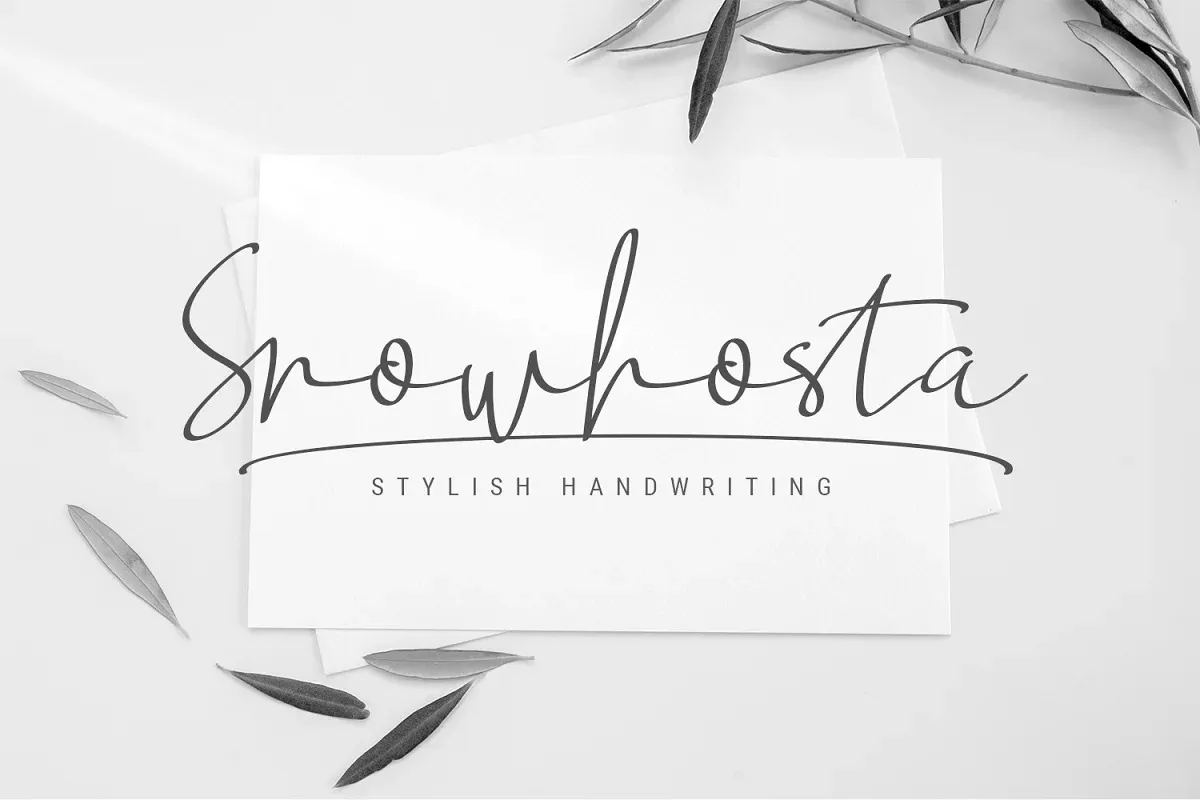
A fonte Snowhosta é uma elegante e bem equilibrada fonte de script, cuidadosamente criada pela Fontcastle para designers apaixonados por estilo moderno. Cada letra exibe um toque único e belo, garantindo que seu design brilhe com vida. Definida por curvas suaves e perfeitas para o branding fashion ou editoriais, Snowhosta encanta seus usuários com sua autenticidade. Este é um ótimo recurso para quem quer criar cartões de agradecimento adoráveis, artes de estação elegantes, postagens em redes sociais chamativas e convites de casamento incrivelmente bonitos. Com apenas uma olhada na fonte Snowhosta, você se sentirá compelido a explorar suas possibilidades infinitas no design gráfico.